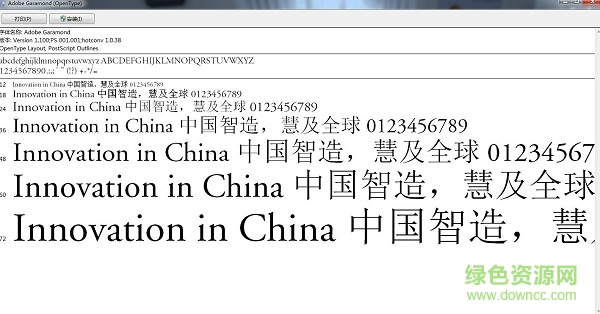
adobe garamond字體是一款可讀性非常出色的英文襯線字體,橫細(xì)豎粗,外觀精致,容易識(shí)別,多用于各類(lèi)印刷報(bào)告或書(shū)籍中,歡迎大家免費(fèi)下載!
印刷字體造型上注重通用性與規(guī)格化。是字體設(shè)計(jì)的一個(gè)重要部分。
襯線字體和非襯線字體是歐美人提出的概念,襯線字體是指有些偏藝術(shù)設(shè)計(jì)的字體,在每筆的起點(diǎn)和終點(diǎn)總會(huì)有很多修飾效果,非襯線字體是指粗細(xì)相等、沒(méi)有修飾的字體,實(shí)際上這個(gè)也適用咱們的漢字。
字體設(shè)計(jì)的功能:信息傳播與視覺(jué)審美。